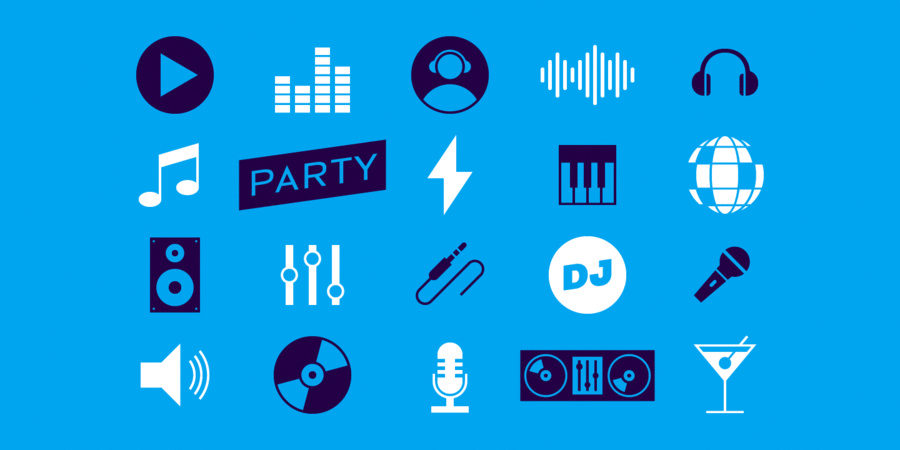
Гарнітура Electrónica – це геометричний шрифт без зарубок з гострими деталями та грайливими формами для веселого й невимушеного використання. Electrónica була задумана як шрифт для логотипів, заголовків та акціденціі, а також для коротких текстових блоків. Electrónica складається з 12 накреслень, 8 з яких містять символи латиниці й кирилиці, капітель, лігатури, а 4 накреслення безкоштовні для використання на умовах десктоп-ліцензії. Шрифт розробив Пабло Балселлс в 2019 році.
Асоціації з сімейством шрифтів ElectronicaОсобистість і характер гарнітури:
легкий, модний, тонкий, оригінальний, дзвінкий, артистичний, сучасний, міський, музичний, популярний, точний, делікатний, прохолодний, ефектний, невагомий, прозорий, інтимний, крихкий, повітряний, скляний, гострий, дротяний, холодний, електронний, худий, ламаний, незграбний, колючий, динамічний, виразний, молодіжний, позитивний, свіжий, твердий, чіткий, стійкий, яскравий, помітний, мотивуючий, інженерний, архітектурний, переконливий, стабільний, серйозний, надійний, впевнений, сильний, індустріальний, техногенний, гучний, урбаністичний, сталевий, міцний, штучний, машинний, залізничний, амбітний, суворий, грубий, робочий, мужній, важкий, потужний, солідний, промисловий, активний, радянський, монументальний, брутальний, жорсткий, кричущий, неоновий, клубний, манірний, дотепний, грайливий, глянцевий, тусовочний, ритмічний, святковий, привабливий, кислотний, танцювальний, хіпстерський, радісний, сексуальний, нічний